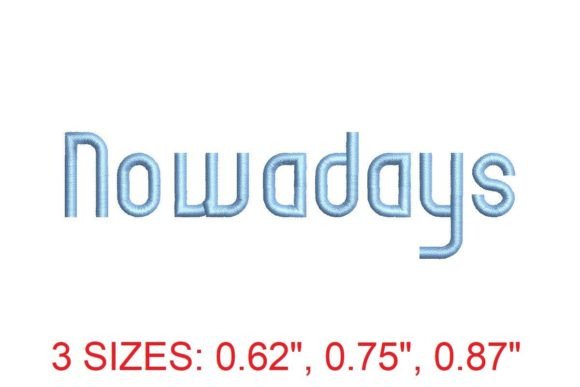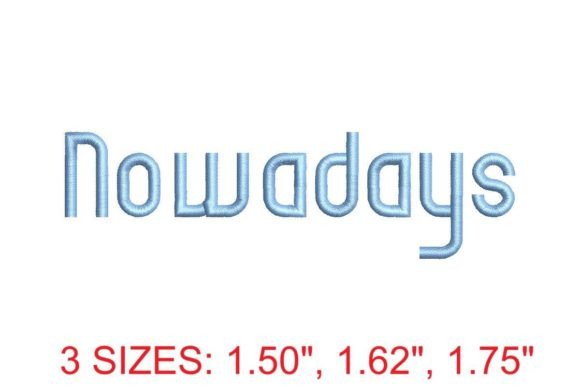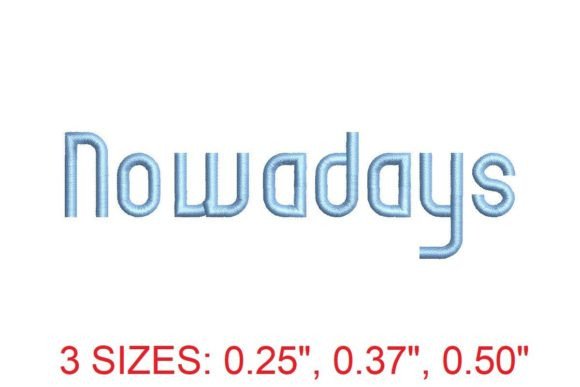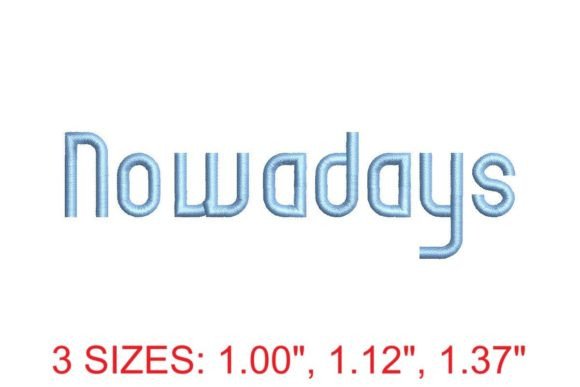
Nowadays Font
Mencari elemen reka bentuk yang sesuai boleh menjadi mencabar, tetapi Nowadays Font menawarkan koleksi luar biasa yang menaik taraf karya anda serta-merta.
Dicipta dengan ketepatan, Nowadays Font menyediakan vektor yang bersih, tipografi yang licin dan lesen komersial untuk ketenangan fikiran.
Sama ada anda mencipta produk POD (Print on Demand), jemputan perkahwinan atau grafik media sosial, Nowadays Font amat bersesuaian.